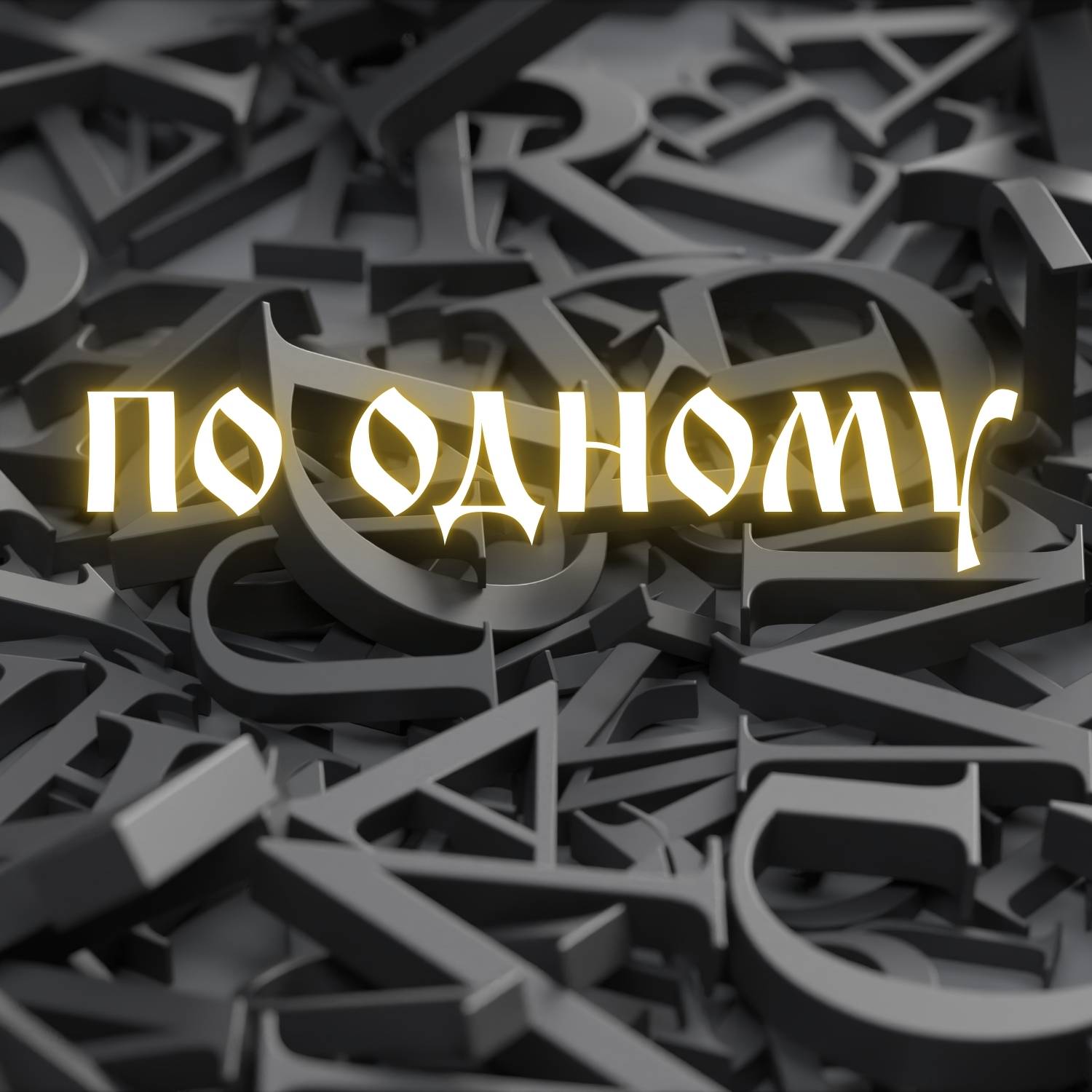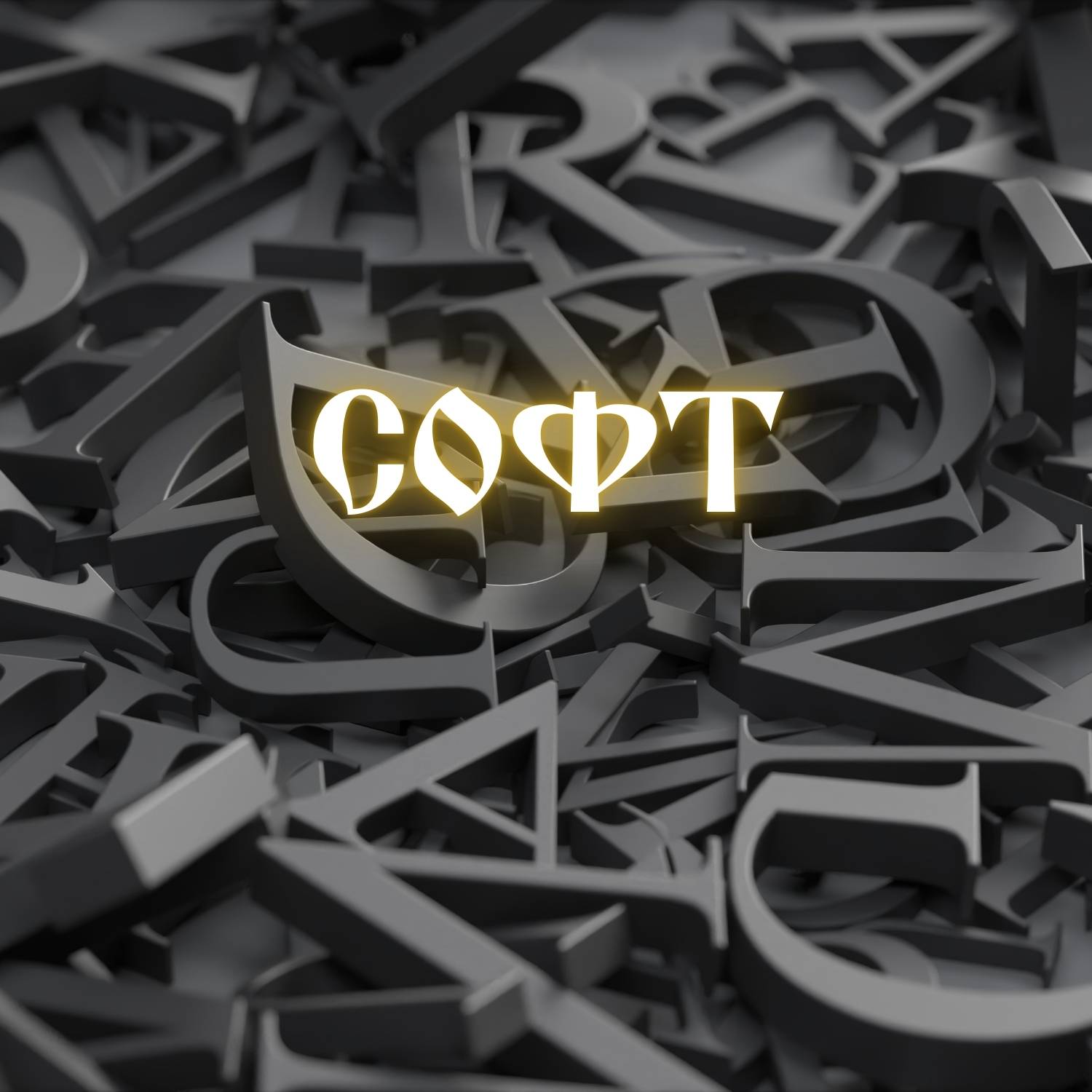
Шрифты и Церковно-славянский язык
Церковнославя́нский язы́к — славянский язык христианского богослужения и письменности, сформировавшийся из старославянского языка. Традиционный славянский язык богослужения, употребляемый Православной церковью в Болгарии, Сербии, Черногории, Северной Македонии, Польше, Белоруссии, на Украине и в России, а также отчасти в Молдавии, Словакии и Чехии (исторически также в Валахии). В большинстве церквей используется наряду с национальными языками.
Распространение церковнославянского языка в разных славянских странах сопровождалось его адаптацией к особенностям местных славянских языков. В результате уже с IX–X веков возникали территориальные разновидности языка — его изводы (варианты).
Наиболее распространённая форма из ныне употребляемых — современный синодальный извод церковнославянского языка, используемый как литургический язык Русской православной церковью и некоторыми другими религиозными объединениями. Кроме Русской православной церкви, церковнославянский язык — основной богослужебный язык славяно-византийского обряда Российской грекокатолической церкви, употребляется, наряду с украинским, в Украинской грекокатолической церкви, наряду с белорусским — в Белорусской грекокатолической церкви. До реформ 1960—1970-х годов, наряду с латинским, употреблялся в некоторых местах в Хорватии, в Католической церкви.
По аналогии с латынью, активно использующейся в медицине, биологии, юриспруденции, а также в Католической церкви, но не являющейся разговорным языком, церковнославянский язык также является мёртвым языком, используемым только в отдельной церковной книжно-письменной сфере, в гимнографии и ежедневном богослужении в некоторых православных и грекокатолических церквях.
Старославянская кириллица является основой письменности многих современных языков.
Название
Термин «церковнославянский язык» впервые появился в «Рассуждении о славянском языке» А. X. Востокова (1820) и указывает на преимущественно церковную сферу его использования. В филологических текстах древних славянских книжников и филологов Нового времени церковнославянский язык назывался «словенский», «славянщина». В филологической литературе до сих пор используется термин «славянизмы» в значении «церковнославянизмы». Поскольку церковнославянский язык развивался из старославянского и нет принципиальных различий между тем языком, который создали Кирилл и Мефодий, и тем, каким он становился в дальнейшем, в понятие «церковнославянский язык» нередко включается и старославянский язык.
История
Перевод богослужебных книг Кириллом и Мефодием. Миниатюра из Радзивилловской летописи, конец XV века.
Старославянский язык (ранняя форма церковнославянского) восходит к солунскому диалекту древнеболгарского языка, родному для создателей письменного старославянского языка Кирилла и Мефодия, хотя за время своего бытования он подвергся грамматическим и фонетическим упрощениям (в частности, исчезли носовые и редуцированные гласные) и сближению с живыми языками стран, в которых он бытует. Впервые был введён в культурный обиход в Великой Моравии.
В Моравии Кирилл и Мефодий вместе с учениками переводили церковные книги с греческого на старославянский язык, обучали славян чтению, письму и ведению богослужения на старославянском языке. В 869 году в Риме Кирилл умер, а Мефодий в следующем году вернулся в Моравию уже в звании архиепископа. После смерти Мефодия его преемником в Моравии стал его ученик Горазд Охридский.
При Горазде противники славянской письменности в Моравии добились у папы Стефана V запрещения славянского языка в церковной литургии, а ученики Мефодия были изгнаны из Моравии. Несмотря на это, распространение письменности на старославянском языке в Моравии и Чехии сразу не прекратилось. Известны литературные памятники, написанные в этих странах глаголицей на старославянском языке в X и XI веках — Киевские листки, Пражские отрывки и другие.
Ученики Мефодия, покинув Моравию, частично отправились к хорватам, а частично — в Болгарию, где продолжили дело развития славянской письменности. Именно Болгария и стала в конце IX века центром распространения письменности на старославянском языке. Здесь сформировались две крупных школы — Охридская и Преславская, в которых творили знаменитые болгарские книжники — Климент Охридский, Наум Охридский, Иоанн Экзарх, Константин Преславский и Черноризец Храбр.
В X веке, вместе с принятием христианства, старославянский в качестве литературного языка начинает использоваться в Древнерусском государстве, где образуется Древнерусский извод церковнославянского языка.
Первой печатной книгой на церковнославянском языке стал хорватский Ⰿⰹⱅⰰⰾⱏ ⱂⱁ ⰸⰰⰽⱁⱀⱆ ⱃⰹⰿⱅⰽⱁⰳⰰ ⰴⰲⱁⱃⰰ (Misal po zakonu rimskoga dvora), изданный в 1483 году глаголицей.
Письменность
Памятники старославянской и церковнославянской письменности известны как на глаголице, так и на кириллице.
На письме современный церковнославянский язык использует кириллицу. Церковнославянская азбука содержит около 40 букв, некоторые из которых представлены более чем одним вариантом написания (неопределённость с числом букв связана с неоднозначностью границы между разными буквами и разными вариантами одной буквы). Используются многочисленные надстрочные знаки (три вида ударения, придыхание, три сочетания придыхания с ударениями, ерок, кендема, краткая, простое титло, разнообразные буквенные титла). Знаки препинания несколько отличны от русских: так, вместо вопросительного знака используется точка с запятой, а вместо точки с запятой — двоеточие. Различаются прописные и строчные буквы, употребление которых может быть либо аналогичным русскому, либо следовать древней системе, в которой с большой буквы писалось преимущественно только первое слово абзаца.
А а Б б В в Г г Д д Є є, е Ж ж Ѕ ѕ
а҆́зъ бꙋ́ки вѣ́ди глаго́ль добро̀ є҆́сть живѣ́те ѕѣлѡ̀
Много общего в синтаксисе причастий греческого и церковнославянского языков: большей частью эти схождения опирались на явления живого славянского языка; греческое влияние способствовало распространению некоторых конструкций (глагол «бы́ти» с причастием, причастия после фазовых глаголов и др.), привело к сравнительно частому употреблению самостоятельного дательного падежа на месте греческого самостоятельного родительного падежа; в отдельных случаях фиксируется и калькирование греческих причастных конструкций, но оно не закрепилось и осталось в рамках отдельного употребления, а не системы языка.